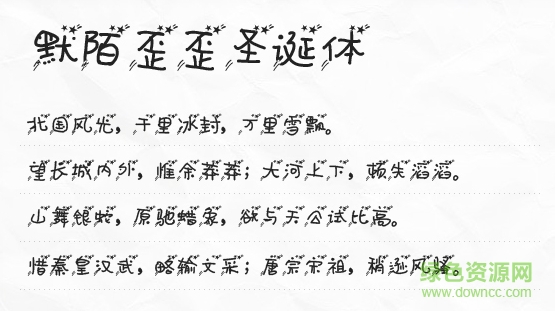
默陌圣誕節(jié)字體是默陌字庫(kù)專為圣誕推出的特色卡通字體,延續(xù)了默陌歪歪字體的特色,加入了雪花流星的點(diǎn)綴,給人撲面而來(lái)的圣誕節(jié)氣息,快來(lái)綠色資源網(wǎng)裝飾你的文字吧!
默陌歪歪圣誕體是在默陌歪歪體上增加了多種點(diǎn)綴和裝飾,讓文字內(nèi)容變得更加出彩,顯得更加豐富和生動(dòng),可以使用在節(jié)日祝福和海報(bào)設(shè)計(jì)等場(chǎng)合中,抓緊時(shí)間體驗(yàn)吧!
圣誕節(jié)馬上就要來(lái)臨了,很多設(shè)計(jì)師都會(huì)尋找屬于這個(gè)節(jié)日的字體來(lái)裝飾他們所設(shè)計(jì)的作品。本站推薦的默陌圣誕節(jié)字體讓你真切的感受到圣誕節(jié)的氣氛,無(wú)論中文還是英文書寫,都很有特色,給你與眾不同的設(shè)計(jì)體驗(yàn)!